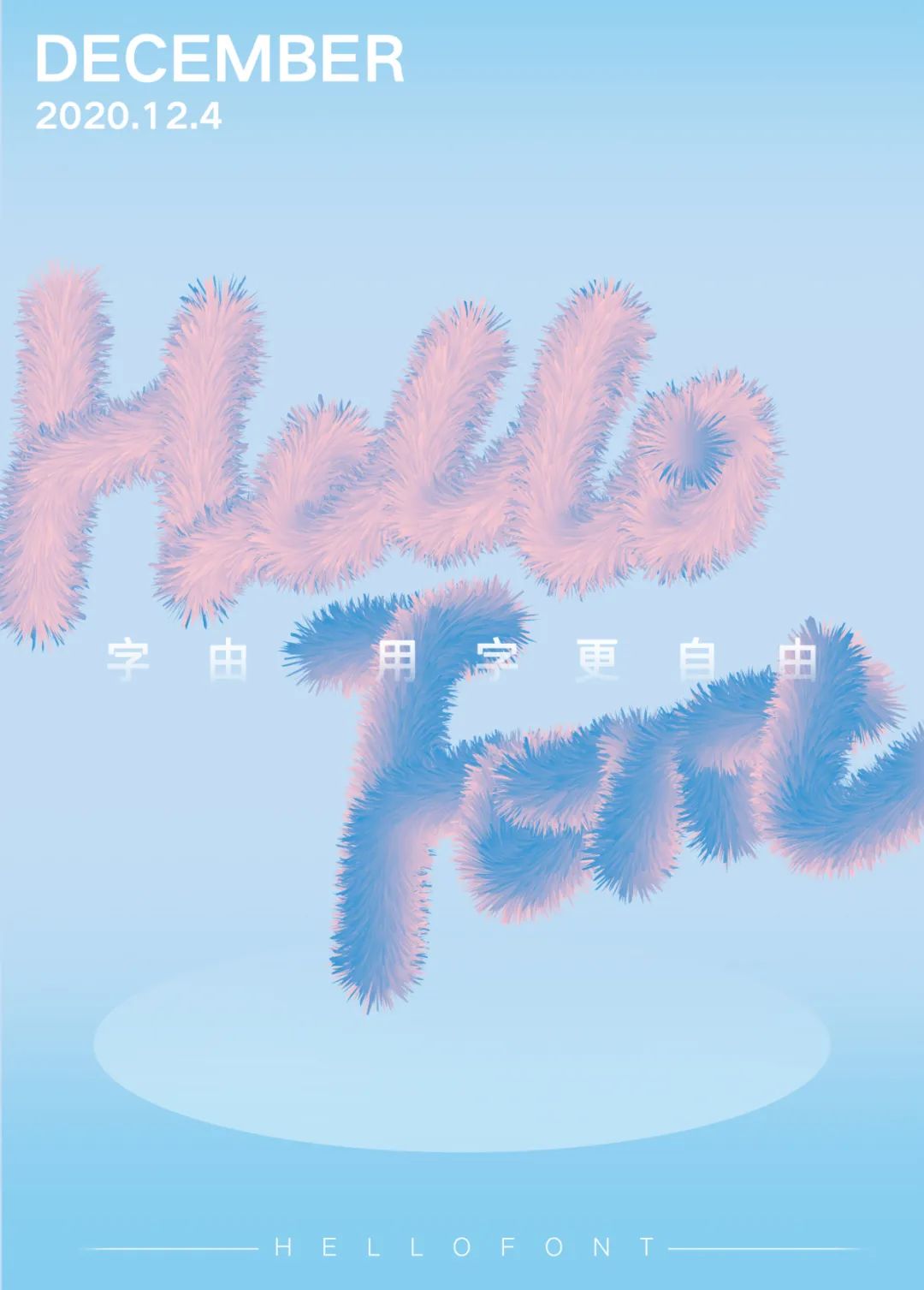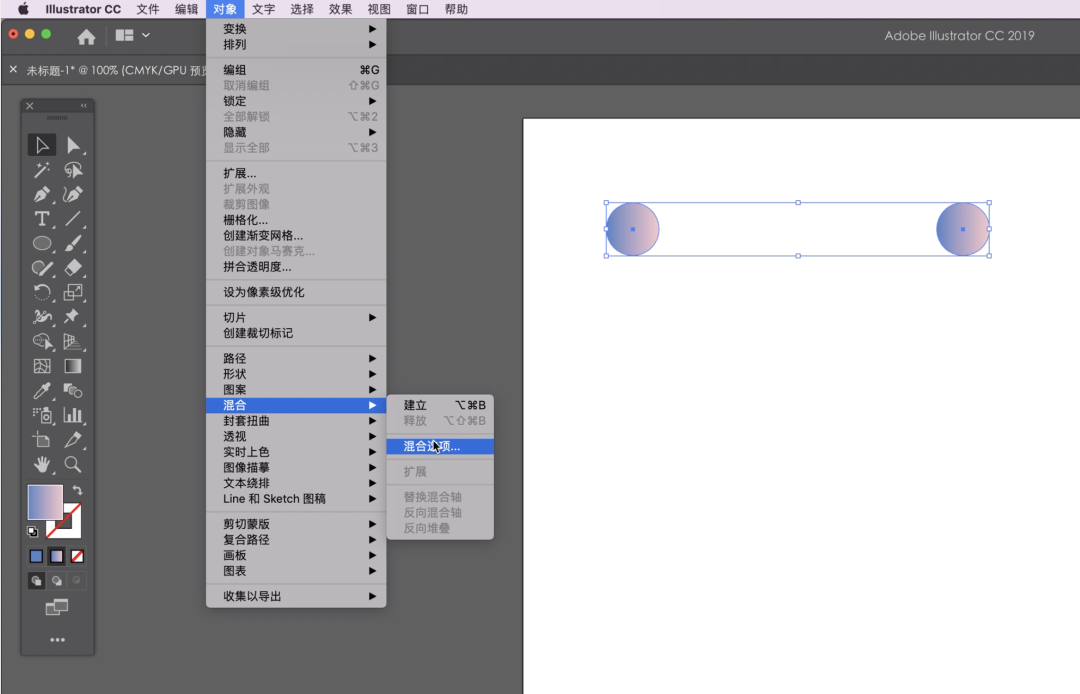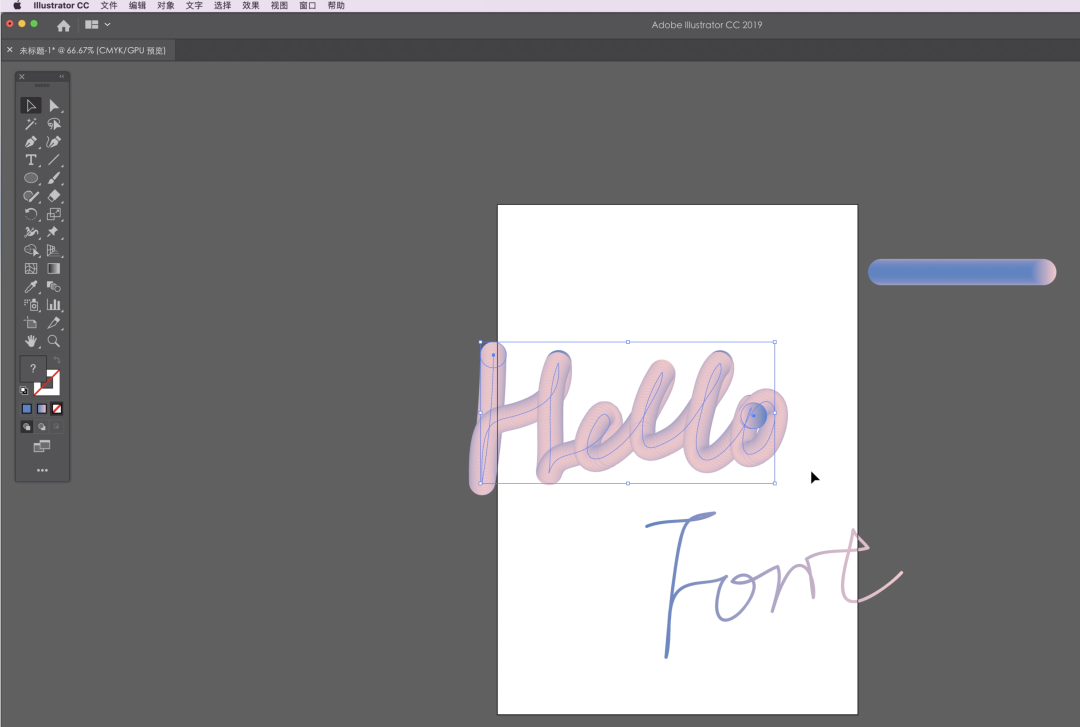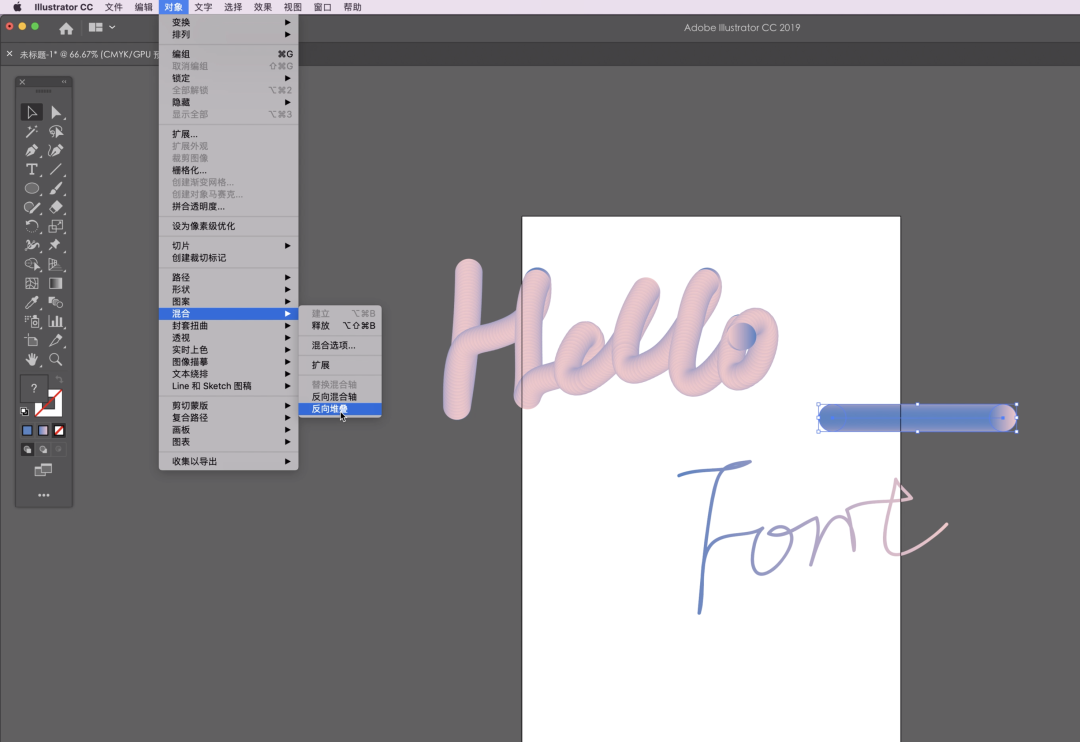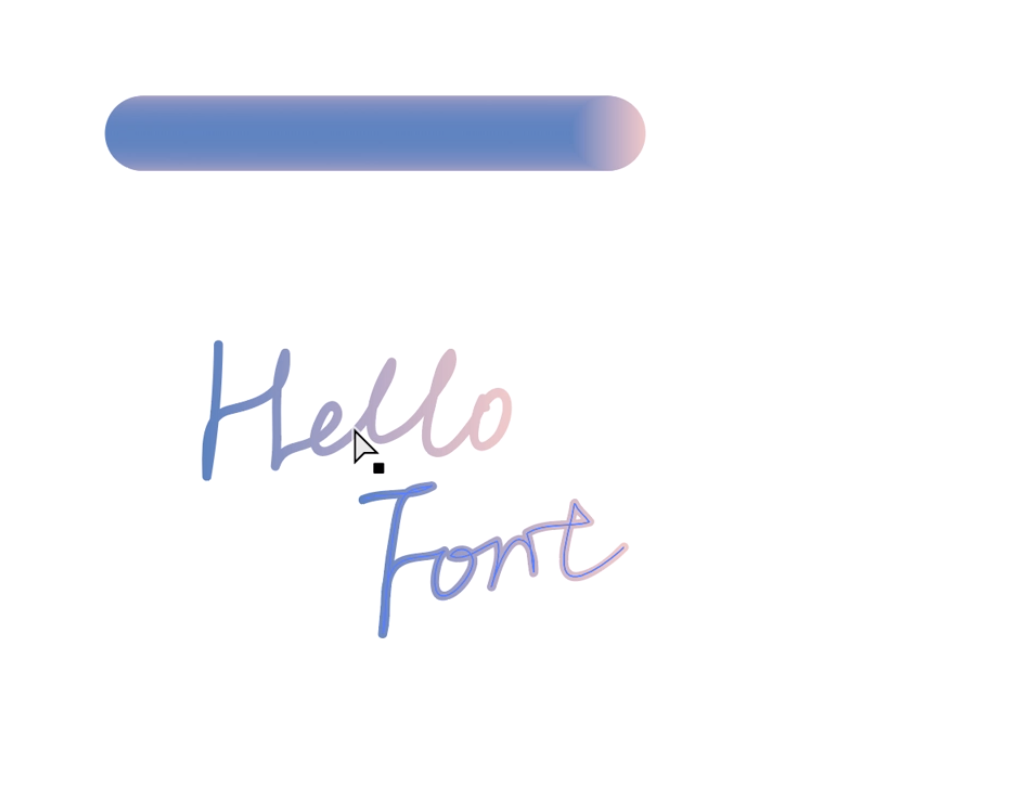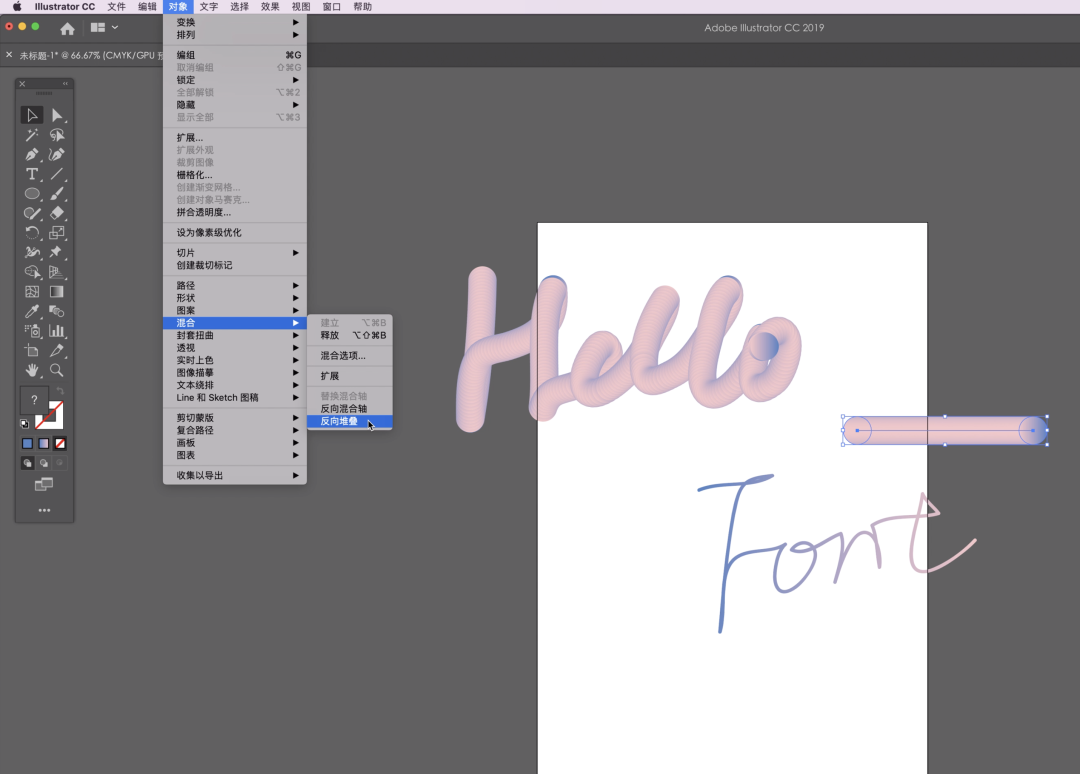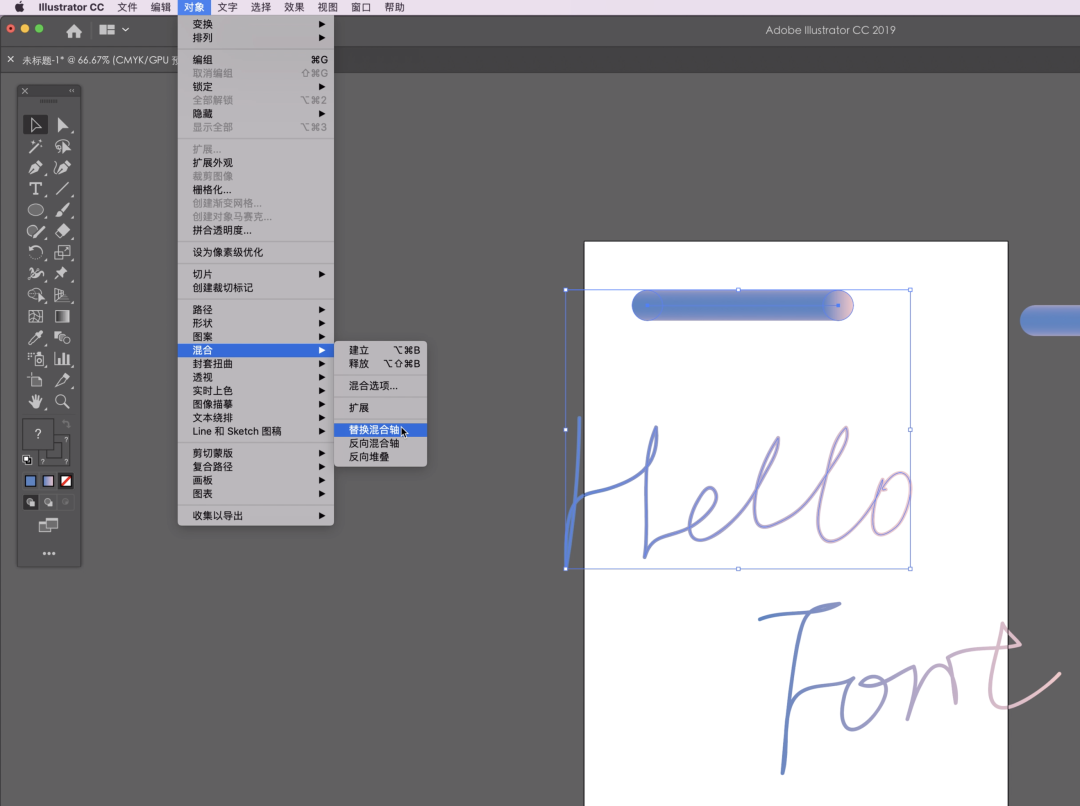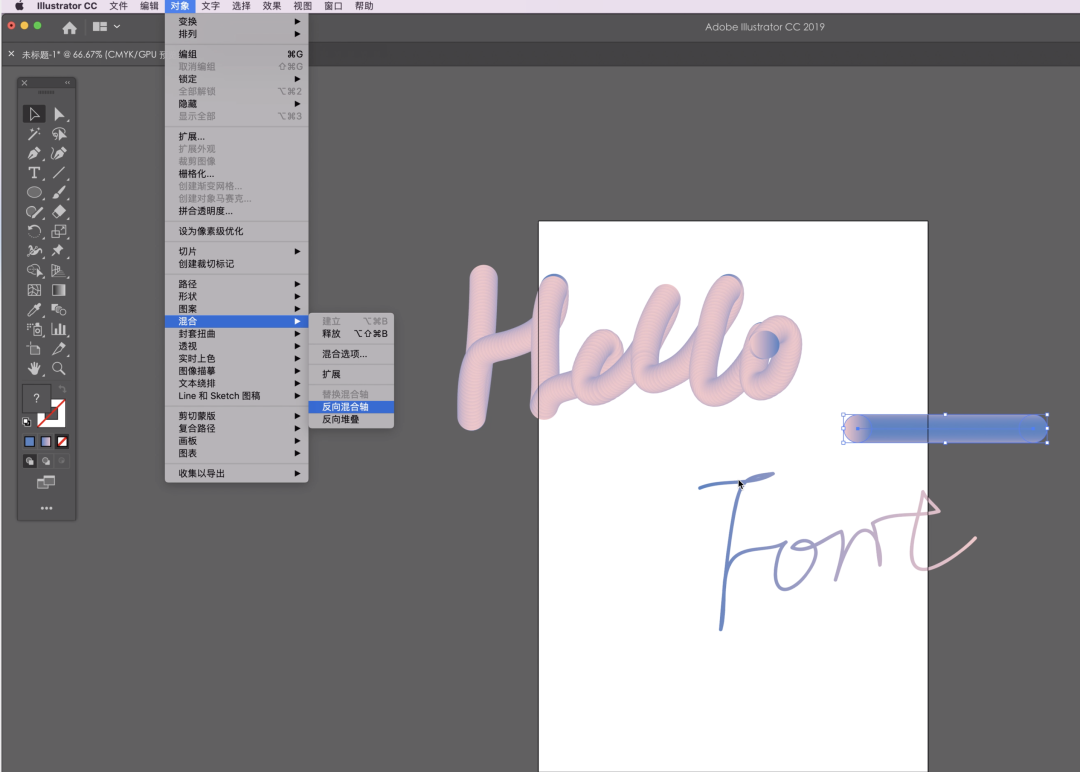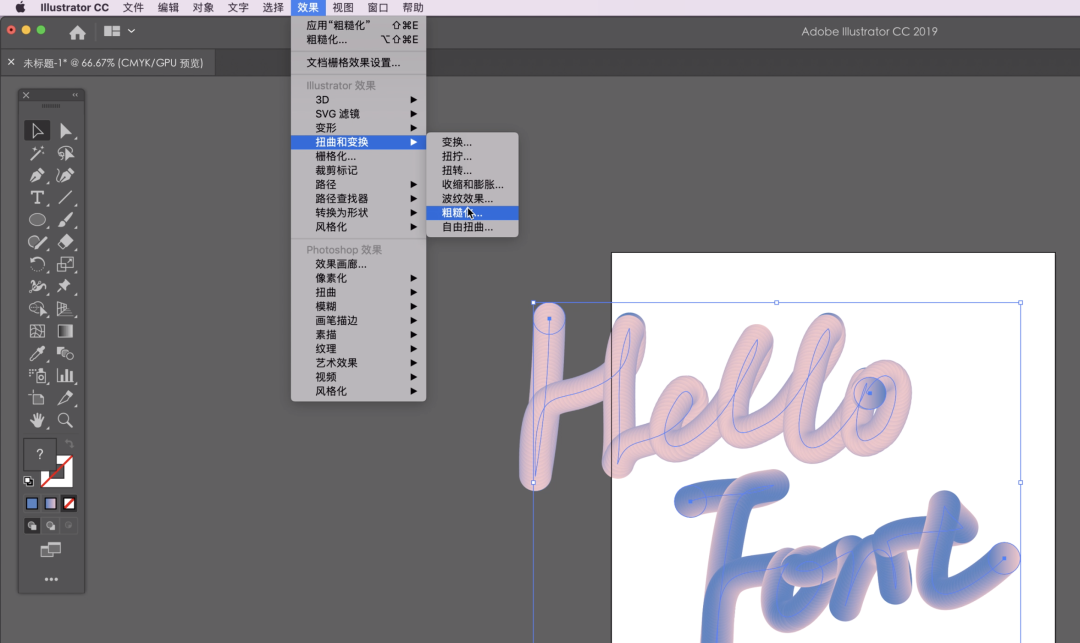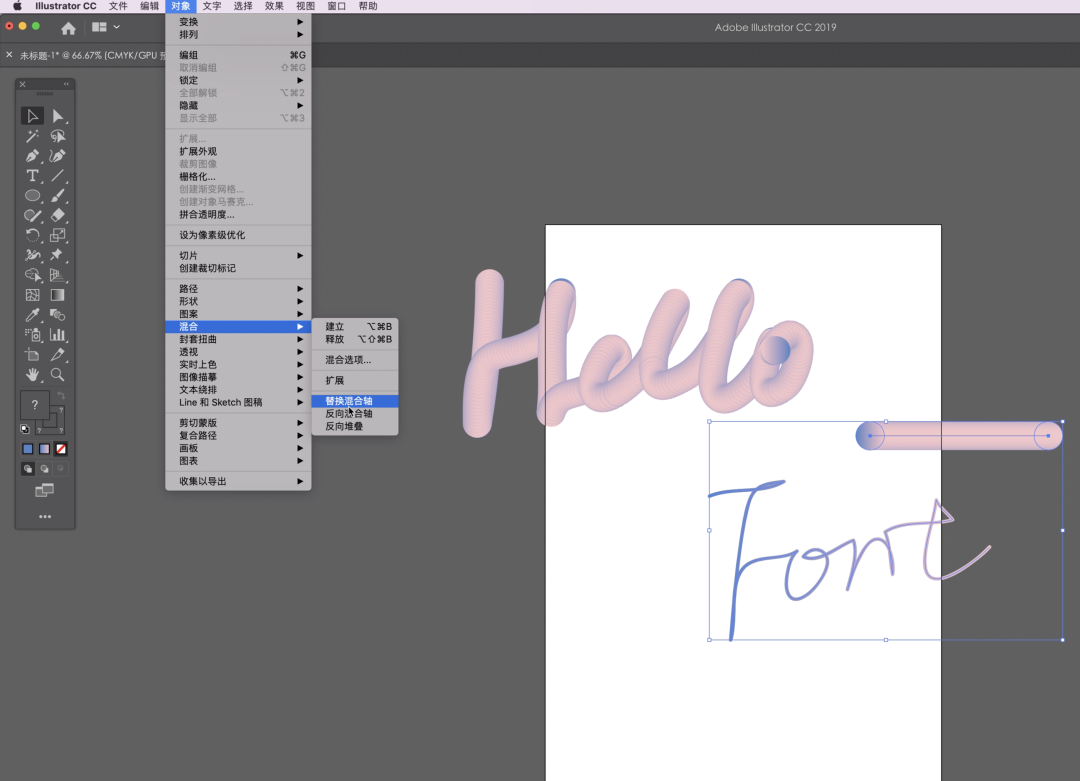
汉仪圆绒体字体介绍,一个毛茸茸的字体分享
最近天气太冷了,所以特别喜欢那种毛茸茸的字体设计,感觉整个人都暖和起来了,比如汉仪圆绒体(单独付费授权)。嗯挺好看的,但是毛还不够多不够长,那就自己做一个吧,简单的AI就搞定,⛄️先看看效果~跳出混合选项的界面,选择指定的步数,参数调整为400(步数越高越丝滑~)。用画笔工具一笔写出你想要的文字,发挥不稳定真的很痛苦……复制一个渐变条,然后全选文字和其中一个渐变条,点击对象-混合-替换混合轴。想要Font变成反向的渐变色,可以选择剩下的渐变条,点击对象-混合-反向堆叠。全选渐变条和Font,选择对象-混合-替换混合轴。下面开始做毛绒效果⛄️,全选文字点击效果-扭曲和变换-粗糙化。弹出参数界面,勾上预览,就可以自己调整合适的参数啦~最后调整一下颜色和版式,再加一点细节~可爱的毛绒字体就出炉啦😺。装饰字体用的点字典黑,其中包含5个家族字,不同粗细满足不同的做图需求~